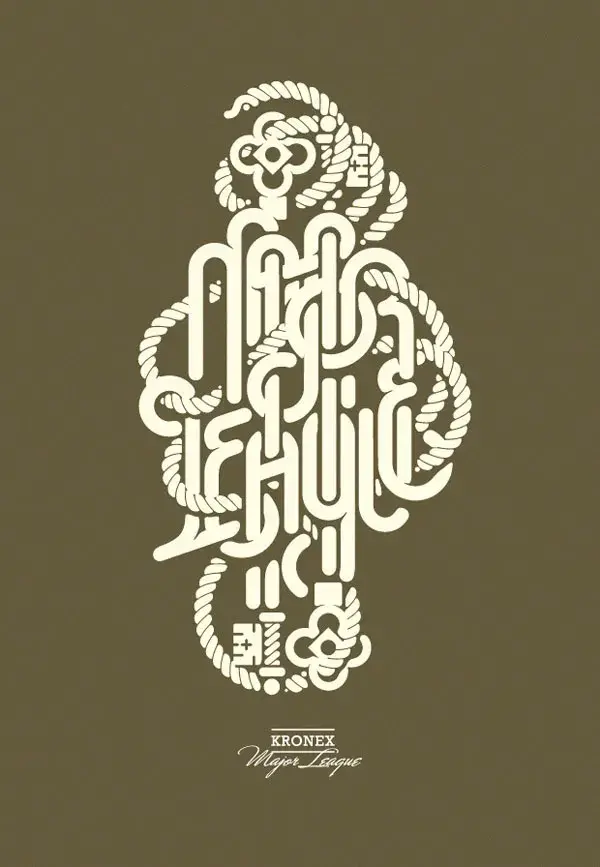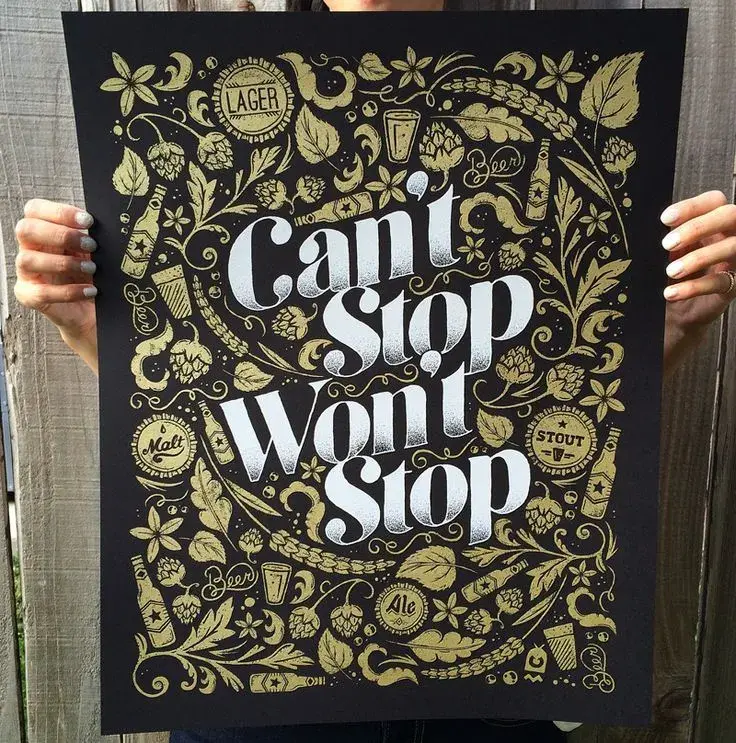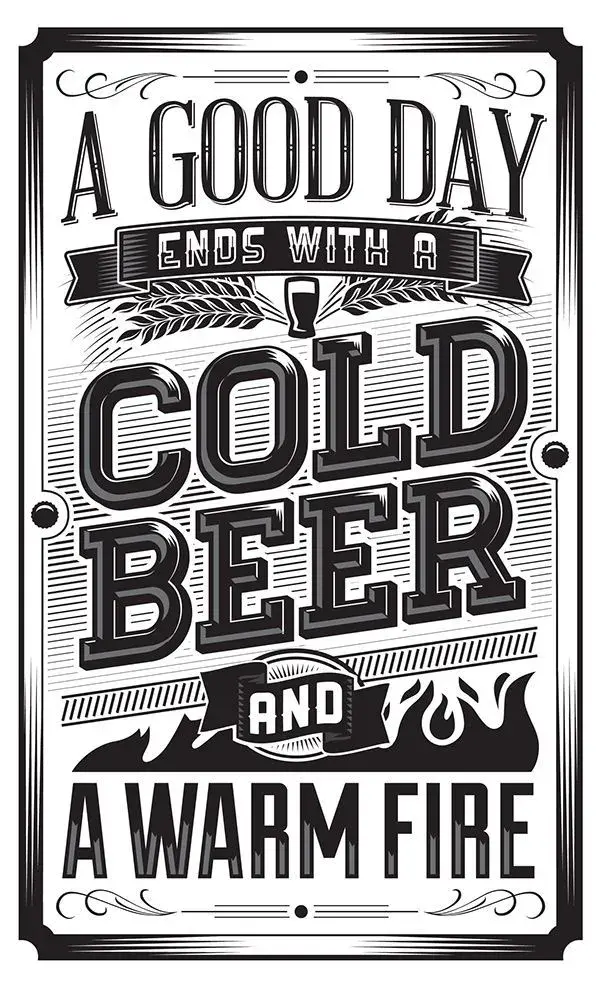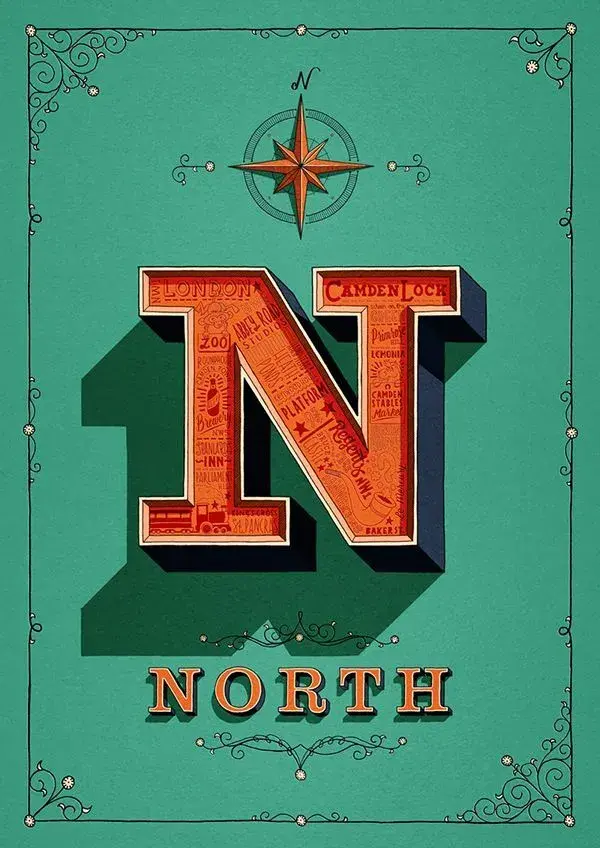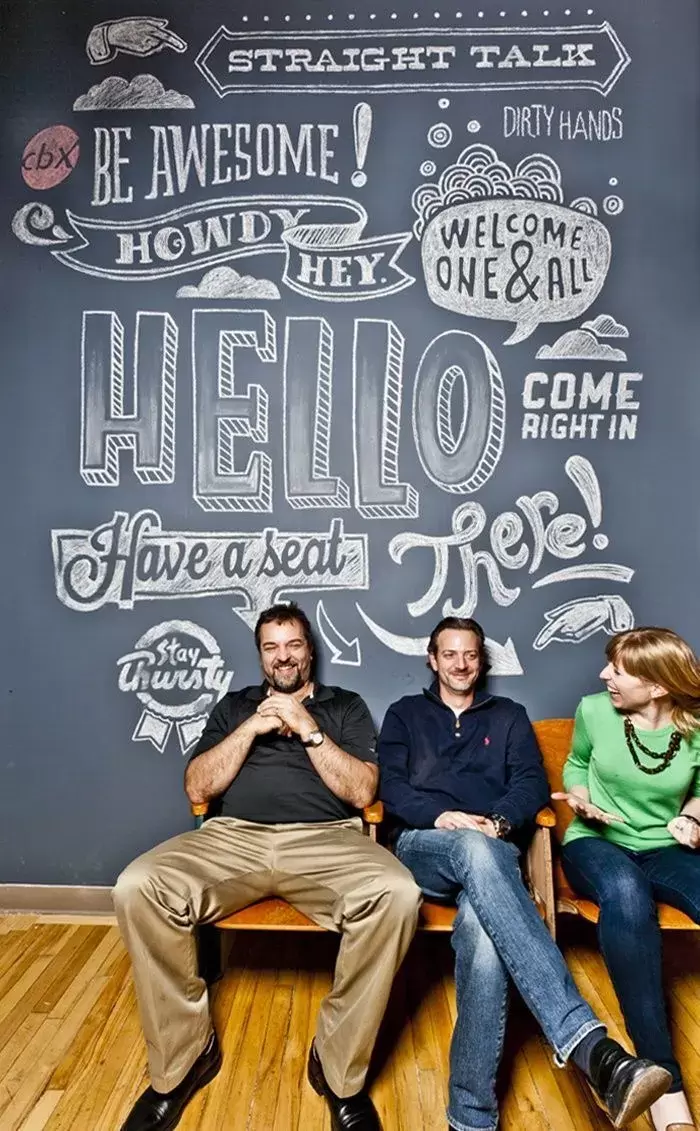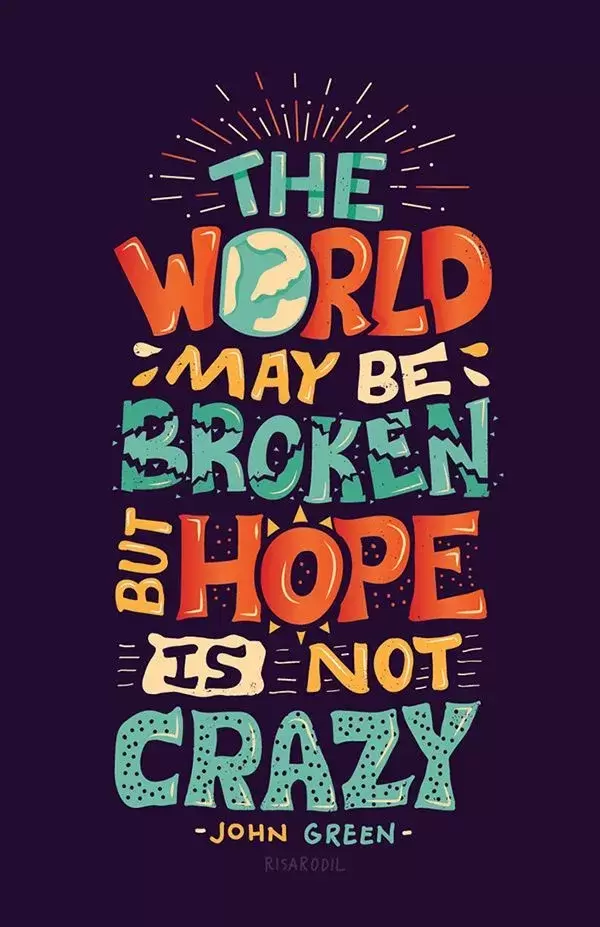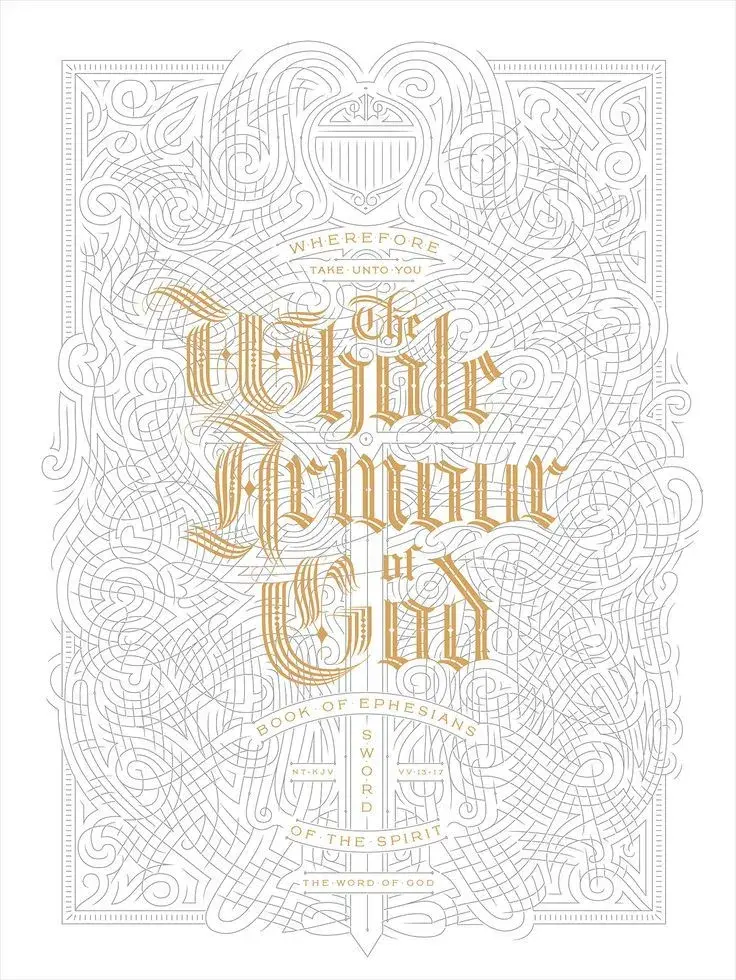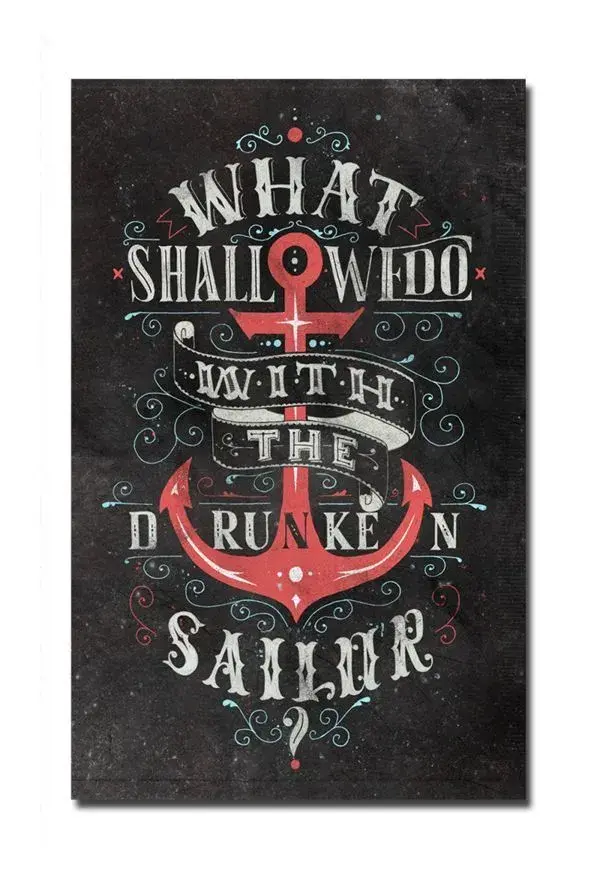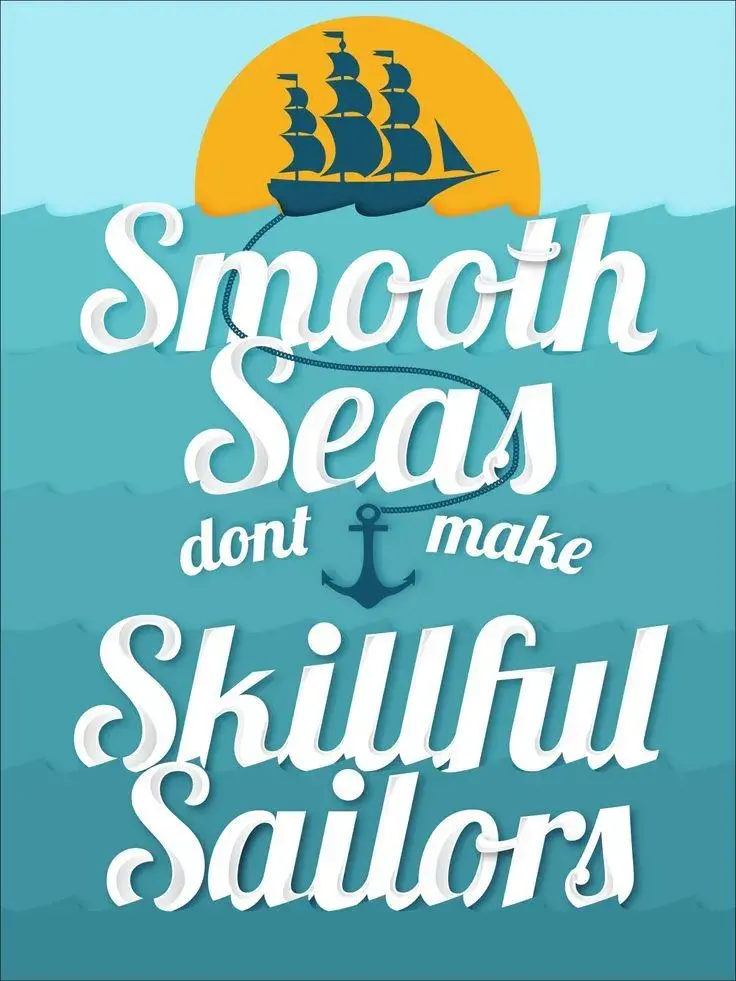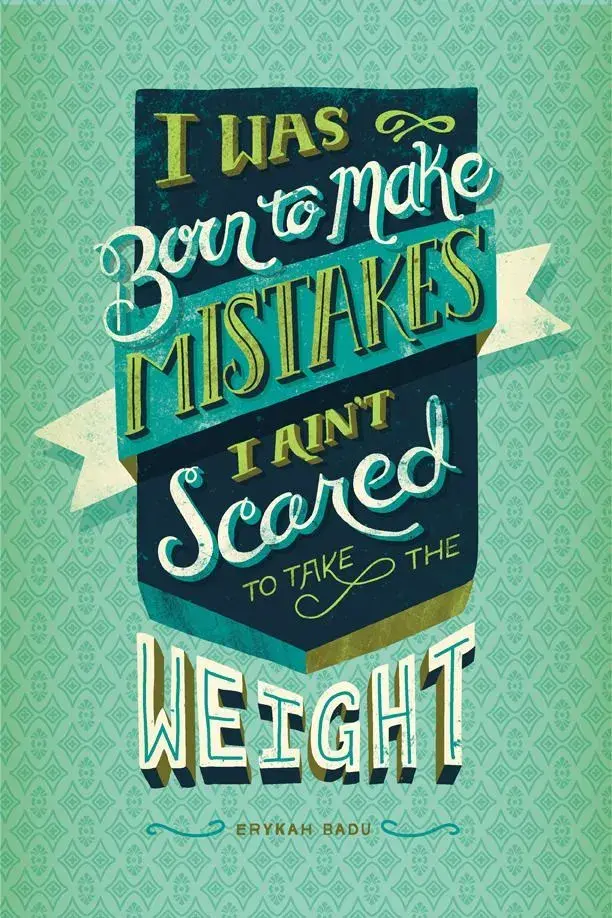
Des typographies originales pour votre inspiration
Pour bien finir la semaine, le BlogDuWebdesign vous propose une bonne dose d’inspiration autour de la typographie originale afin de voir les dernières tendances visuelles qui marquent cette fin d’année.
Nous avons regroupé un medley de créations qui vont de l’affiche, de la carte de visite en passant par le packaging et le croquis.
Le lettering et les typographies manuscrites restent les plus utilisées actuellement, elles donnent une grande variété dans les styles graphiques et permettent de réaliser des affiches très séduisantes.
Great Little Place
Organic Italy Wine Labels
3D Lettering
The Chic Type
CCAA Kids 2014
The Vandalos
Chalk Typographic Motivational Quotes
Cold Beer, Warm Fire
Pavlov Wanderer Poster CA par Pavlov Visuals
Horse (Illustration)
3D Printing
Typography Project (Peep Show rant)
Kevin Cantrell Design
Origin London
CantWont par Nathan Walker
Tropical Winter par Ricardo Garcia
Steven Johnson
Letterings I par Tobias Saul
Hope is Not Crazy Poster par John Green & Vlogbrothers
The Wild Feathers – Hard Times par Jason Carne
Church Mural
Hand Type Vol. 22
Hand Lettering
Gladstone Media
Smooth Sea
Typographic Artworks par André Beato